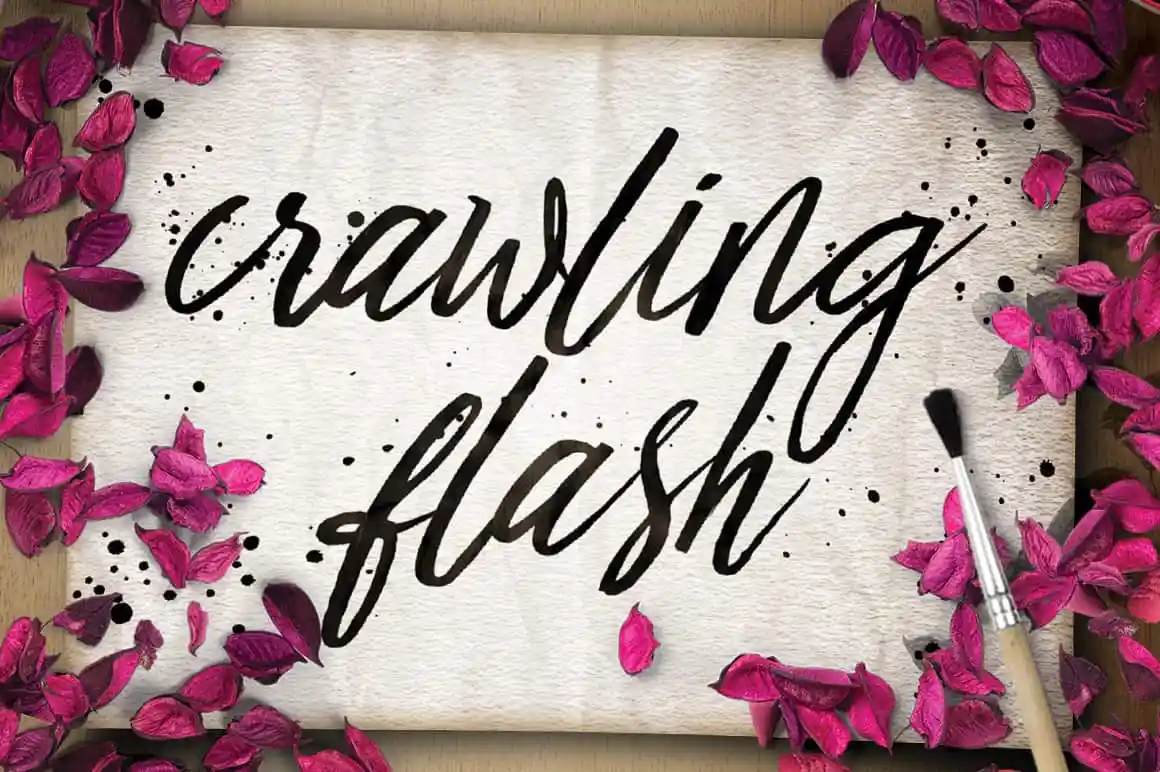
Crawling Flash Script Font – Fonte Grátis
Crawling Flash Script Font
A Crawling Flash Script Font é uma nova face de marca com personalidade perfeita para estilos modernos e trendy. Ela foi projetada para tornar seus projetos, seja ele em cartões de convite, letras para casamentos ou até mesmo designs visuais e literatura artística, mais atrativos e atraentes. Esta fonte brush é ideal para se juntar ao seu estoque de recursos gráficos, oferecendo um toque especial a seus trabalhos. Com sua elegância fluida e características vibrantes, a Crawling Flash é perfeita para criar designs impressionantes em áreas como cartazes, logotipos, letras para casamentos e design vintage pop. Seja qual seja o projeto que está tentando manter atualizado com uma cara nova, a Crawling Flash Script Font certamente fará sua tarefa.